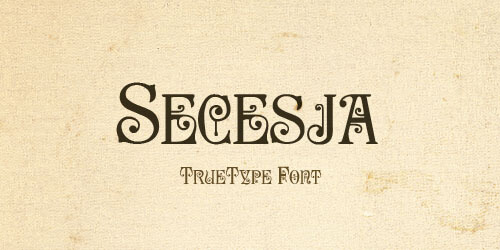
デザインに役立つ、おしゃれでレトロな無料フォント35選!
ウェブデザインにおけるタイポグラフィというのは、普通のデザインを魅力的なものへと変身させることの出来る要素の一つです。最近人気があるトレンドは、レトロなデザインの文字や素材です。
文字やタイポグラフィをきちんと選ぶことで、クライアントにしっかりとデザインの意図が伝わります。この傾向になってきたのはつい最近で、大小様々な規模の企業のデザイン、ブログ、店舗、ポートフォリオなどに主に使用されています。
古風なデザインのフォントにすれば、クリエイティブの効果も高く、他のデザインに差がつくユニークな印象となるでしょう。このデザインが流行ったのはおよそ1910〜30年代頃なので、最近のデザインに取り入れられると昔懐かしいイメージになります。これらの無料フォントを使用すると、ノスタルジックな気分にもなります。ユニークでちょっと変わったデザインにしたいときに、大いに役立つでしょう。
また、強烈で革新的なデザインを作ることも可能です。ネット上には便利な字体がたくさんあり、レトロなフォントも大人気です。
最新のトレンドと混ぜたら、古風で今時のデザインに仕上がること間違いなしです。時間の流れとともに消えていくデザインはあるものの、このレトロ素材のように、再び復活してウェブデザイナーに使用されるようになるものもあります。
レトロ素材が流行ったのは1910年代にも関わらず、デザイナーに使用されるのは過去20年以内のデザインばかりです。筆記体やレタリング文字、ポップなフォントやコンピュータで書いたようなフォントなど、便利でレトロな文字がたくさん編み出されてきました。
これらをデザインに取り入れる際は、配色、素材、レイアウト、背景がフォントに合うかどうかを確認してください。全ての要素がバランスよく配置されることで、より洗練されたレトロなデザインの完成です。
おしゃれでレトロな無料フォント
Sandwich
Titania
Kelvinized
Secesja
Studebaker
Stony Island
Minotaur
Hamburger Heaven
Forty Second Street
Campanile
Minstrel Poster
Sesame
Tall Deco
East Market
Carnivalee Freakshow
Diner Regular
Circus Ornate
Day Poster Black
Showboat
Chi-Town
Nashville
Fletcher Gothic
Matchbook Typefaces
Mailart Rubberstamp
Bazar Medium
20db
Airstream
Seaside Resort
Parisian
Bobel
Fusty Saddle
Brandon Grotesque